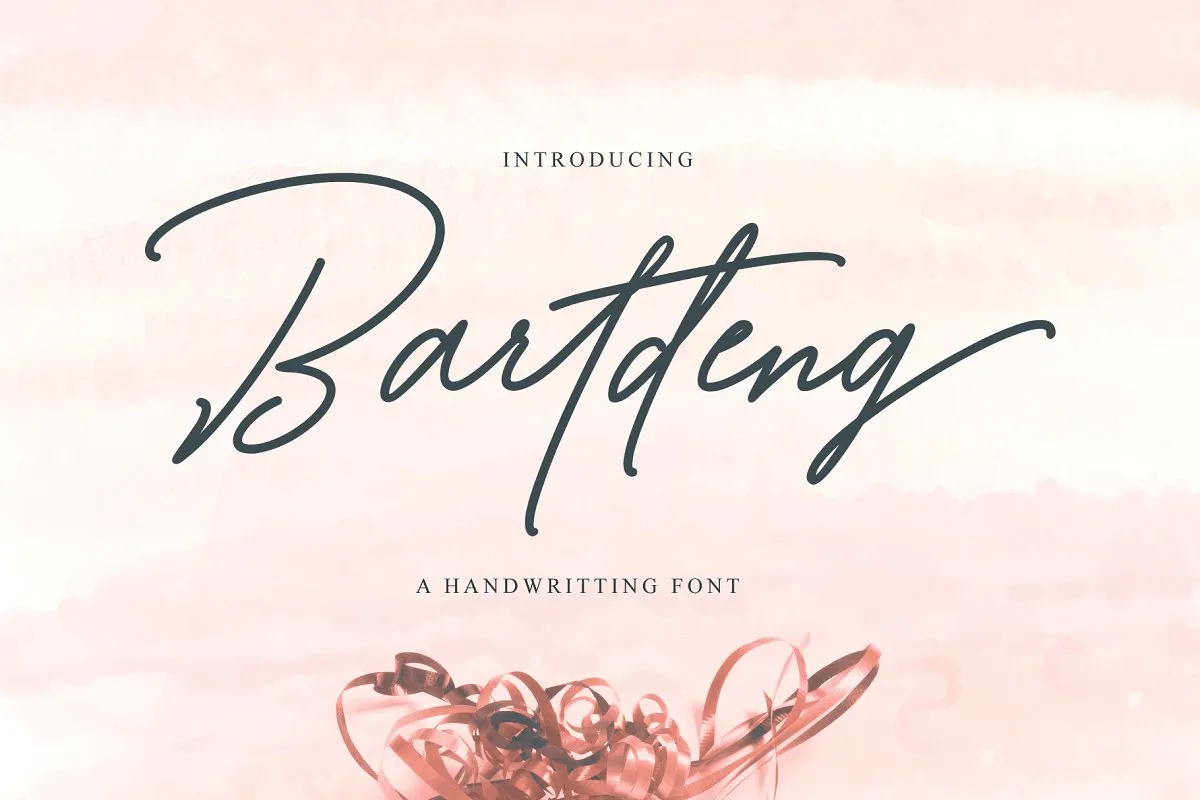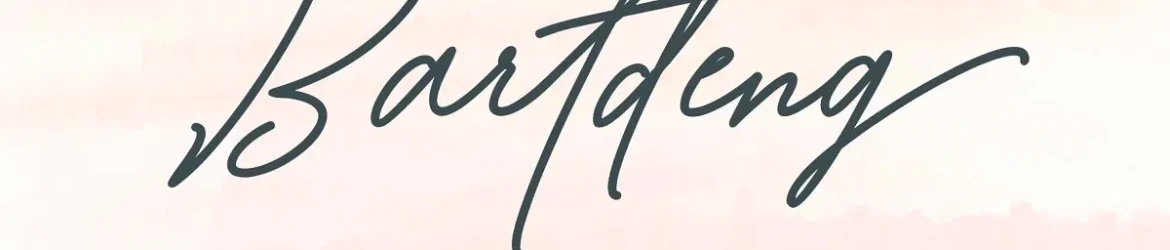
Bartdeng Handwritten Font – Download Grátis
Bartdeng Font é uma elegante tipografia escrita a mão que combina elementos modernos com a naturalidade do traço humano. Ideal para quem deseja destacar seu texto, este fonte foi projetado com cuidado, oferecendo letras perfeitas e um estilo de escrita moderno. Com Bartdeng Font, você encontra uma tipografia única, pronta para diversas aplicações como logomarcas, assinaturas corporativas, convites nupciais, títulos, criação, camisas personalizadas, cartões de visita, plaquettes, panfletos, atas, selos, bonés, cópias e selos. Este opentype inteligente atende a múltiplas necessidades, tornando-se um recurso valioso para designers gráficos e criativos em todo o Brasil.